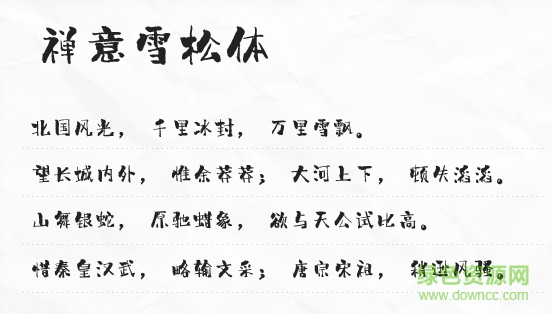
禪意雪松體字體
禪意雪松體字體專為藝術(shù)設(shè)計(jì)而生,該字體撇捺筆畫(huà)粗壯,橫豎筆畫(huà)細(xì)膩,給人非常悠閑自在的感覺(jué),可運(yùn)用于手機(jī)主題,酷炫十足,歡迎到綠色資源網(wǎng)下載使用!
禪意雪松體是一款特色十足的中文字體,具有西方手寫(xiě)字的特色,你可以將其用于海報(bào)設(shè)計(jì)、雜志設(shè)計(jì)、涂鴉設(shè)計(jì)等方面。同時(shí)字體俊逸灑脫,美觀又實(shí)用,深受藝術(shù)創(chuàng)作、排版印刷、編輯設(shè)計(jì)等行業(yè)人士喜愛(ài)!